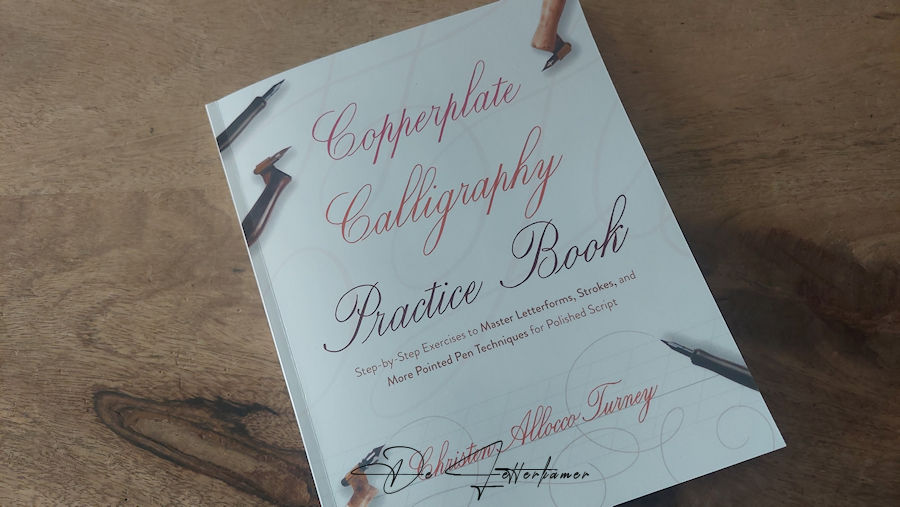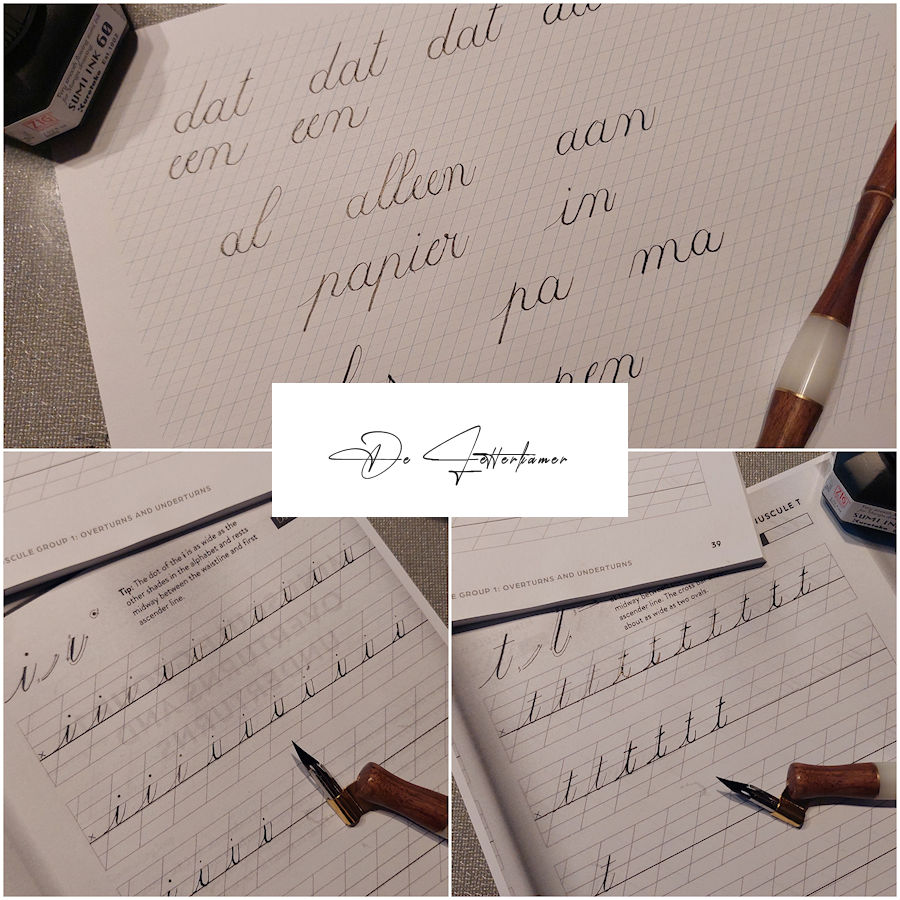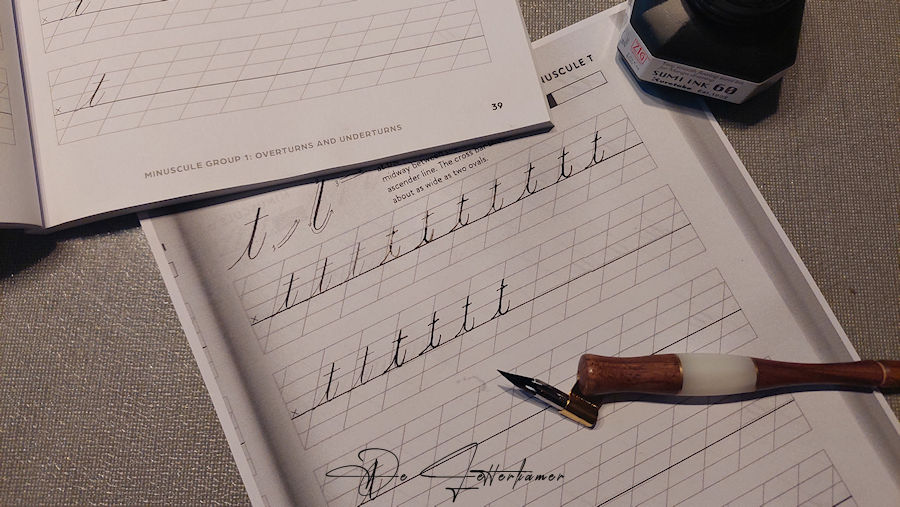
Zo, hier zijn we weer, ik meende al op een blocnote te schrijven maar van zodra ik in het boek keek dacht ik bij mezelf, ik ga toch even proberen met kopieën. Zoals ik eerder gezegd had.
Dit is het oefenboek.
Ik heb er een 4-tal gekopieerd op het gladde printpapier van Clairefontaine. Het papier moet echt glad zijn, de nib blijft heel gemakkelijk hangen in het papier of de inkt vloeit uit. Sinds vandaag heb ik een nieuwe nib Nikko G genomen, de andere ging al niet goed meer, ik vermoed dat ik te hard druk.
De guidelines zijn anders dan dat ik gewoon ben, natuurlijk als je aan zelfstudie doet is het ook wel veel uitzoeken. Ik heb er een aantal gedaan, “de letter i en de letter t“, en dat ging maar toch even wennen, ik heb nogal de neiging om recht te schrijven ook al heb ik een oblique pen.
Hier heb ik de letter “t” geoefend. Daarna de letter “i”.
Je ziet het, helemaal nog niet perfect. Ik vermoed dat het nog maanden zal duren vooraleer ik dit goed zal kunnen.
Ik waande me terug in het 1ste leerjaar, woordjes leren schrijven. Enkele eenvoudige woorden heb ik geprobeerd, ik kon het niet laten om eens een poging te wagen.
De verbindingen tussen de ene letter en de andere letter die weet ik nog niet dat moet ik nog eens bekijken.